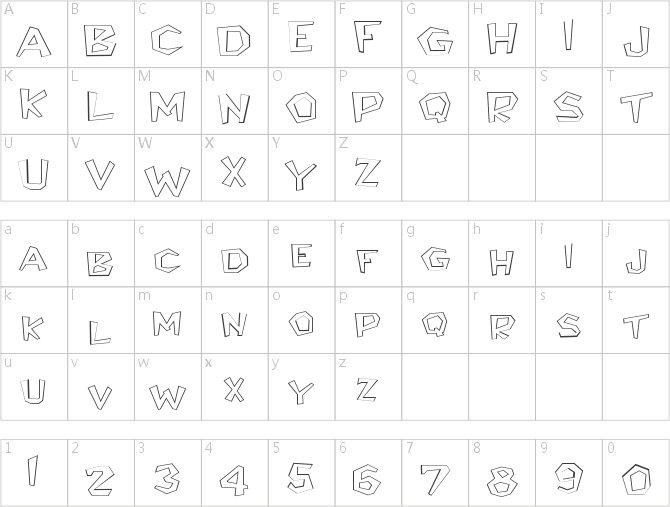
FZ JAZZY 8 HOLLOW EX 詳情頁
FZ JAZZY 8 HOLLOW EX字體字庫是一款讓人賞心悅目、百看不厭的英文字體,適合各類廣告和產(chǎn)品包裝設(shè)計(jì)應(yīng)用,字體大小0.04MB,格式為ttf字體,上傳用戶是Who am I?,作者/版權(quán)方為未知